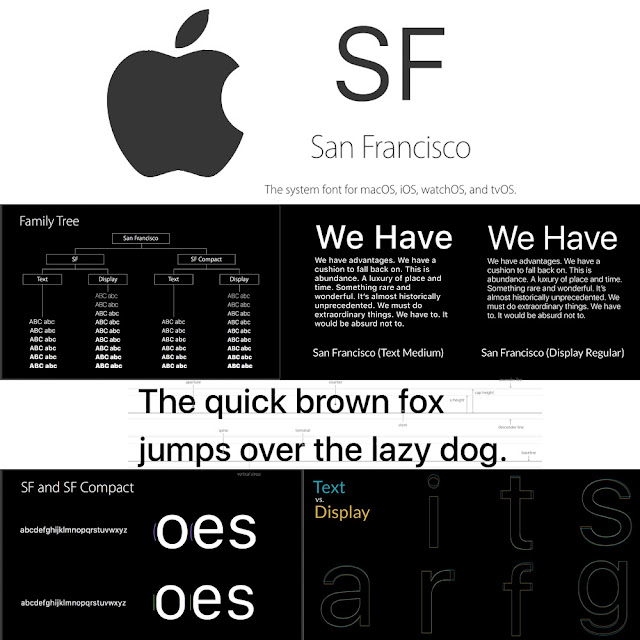
Типографика
Apple предоставляет два семейства шрифтов, которые вы можете использовать в своих приложениях для iOS.
San Francisco (SF). San Francisco — это семейство без засечек, которое включает в себя SF Pro, SF Pro Rounded, SF Mono, SF Compact и SF Compact Rounded. SF Pro — системный шрифт в iOS, macOS и tvOS; SF Compact — системный шрифт в watchOS. Системные шрифты разработаны с учетом визуальной четкости пользовательских интерфейсов платформы, они разборчивы и нейтральн.
New York (NY). New York — это шрифт с засечками, который имеет уникальный тон, разработанный для дополнения шрифтов SF. NY работает одинаково хорошо как в контексте графического отображения (при больших размерах), так и в контексте чтения (при размерах текста).
Поскольку SF Pro и NY совместимы, существует множество способов использовать типографский контраст и разнообразие в интерфейсе iOS, сохраняя при этом единообразный внешний вид. Например, использование шрифтов может помочь вам создать более сильные визуальные иерархии или выделить смысловые различия в контенте.
Разработанные Apple шрифты поддерживают широкий диапазон размеров, стилей и языков, поэтому вы можете создать приятное впечатление от чтения во всем приложении. Когда вы используете стили текста с системными шрифтами, получаете поддержку динамического типа и больших размеров для настроек специальных возможностей, которые позволяют людям выбирать подходящий для них размер текста. Таблицы динамических размеров шрифтов можно загрузить в Sketch, Photoshop и Adobe XD Apple Design Resources для iOS.
SF Pro и SF Compact
Гибкость системных шрифтов помогает добиться оптимальной разборчивости при любом размере и предоставляет широту, глубину, необходимую для точного набора текста во всем приложении.
Поддержка SF Pro и SF Compact:
- Более ста языков с использованием латинского, греческого и кириллического алфавита
- Девять настроек толщины — от сверхлегкого до черного — как вертикальные так и в курсивyst
- Два оптических размера — текст и дисплей
- Переменный межбуквенный интервал, который автоматически корректируется в зависимости от размера текста
- Маленькие прописные, дробные, маленькие и большие цифры
SF Pro Rounded и SF Compact Rounded
Округлый вариант системных шрифтов может помочь согласовать стиль текста с появлением мягких и закругленных элементов пользовательского интерфейса или применить альтернативный типографский стиль.
SF Pro Rounded и SF Compact Rounded поддерживают:
- Более ста языков с использованием латинского, греческого и кириллического алфавита
- Девять настроек толщины — от сверхлегких до черных
- Переменный межбуквенный интервал, который автоматически корректируется в зависимости от размера текста
- Маленькие прописные, дробные, маленькие и большие цифры
SF Mono
SF Mono — это моноширинный вариант Сан-Франциско, то есть шрифт, в котором все символы имеют одинаковую ширину. Используется моноширинный шрифт, когда необходимо выровнять столбцы текста, например, в среде кодирования. Xcode и Swift Playgrounds по умолчанию используют SF Mono.
ПРИМЕЧАНИЕ
SF Pro использует функцию табличной подкладки OpenType для поддержки отображения моноширинных чисел и валют.
SF Mono поддерживает:
- Более ста языков с использованием латинского, греческого и кириллического алфавита
- Шесть настроек толщины — от легкой до сильной — как в обычном варианте, так и курсивом
- Моноширинный интервал по всем толщинам (то есть изменение толщины шрифта не приводит к переформатированию текста)
New York
New York — это классический шрифт с засечками, который вы можете использовать в интерфейсе или для традиционного чтения.
NY поддерживает:
- Более ста языков с использованием латинского, греческого и кириллического алфавита
- Шесть настроек толщины — от обычного до черного — как в обычном варианте, так и курсивом
- Четыре оптических размера — маленький, средний, большой и очень большой
- Переменный межбуквенный интервал, который автоматически корректируется в зависимости от размера текста
Выбор шрифтов для улучшения вашего приложения
По возможности используйте встроенные текстовые стили. Встроенные текстовые стили позволяют выразить контент визуально, сохраняя при этом оптимальную разборчивость.
Helvetica, на смену которому пришли шрифты San Francisco, был создан в Швейцарии в 1957 году, когда не было цифровых устройств. Helvetica уже сейчас широко используется многими компаниями в качестве корпоративного шрифта и, несомненно, будет использоваться в будущем как отличный классический шрифт.
San Francisco, с другой стороны, является современным шрифтом. Он будет динамически менять шрифты в зависимости от контекста. Это своего рода шрифты «Digital Native» для цифровой эпохи.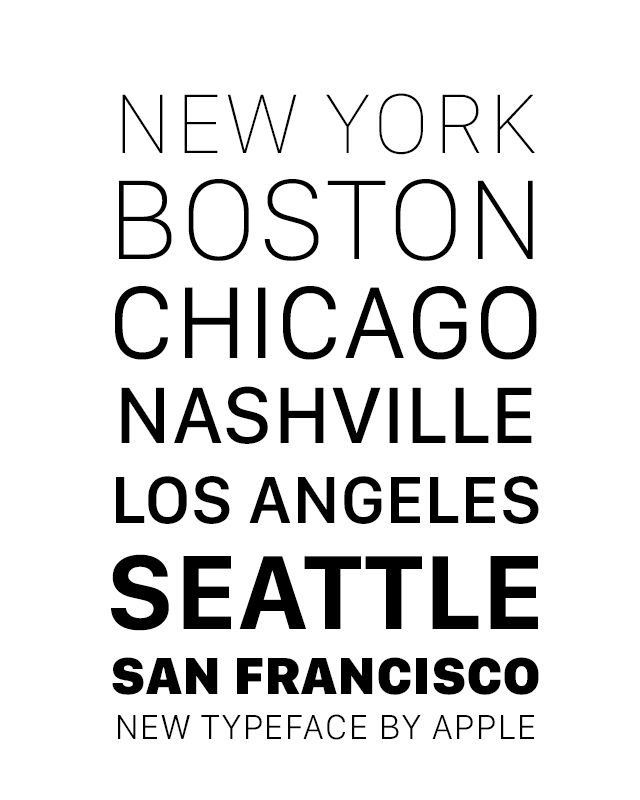